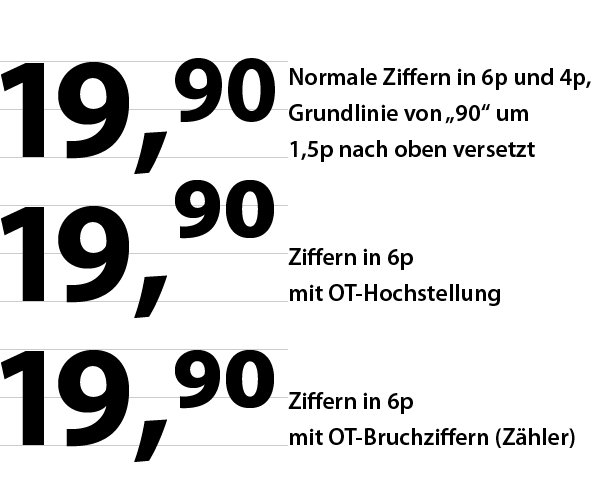
Suche Schrift um Preis auszuzeichnen
ich suche eine geeignete Schrift um Preise auszuzeichnen, siehe Beispiel.
Hat Jemand eine Ahnung welche Schrift in der Grafik verwendet wurde?
Du könntest drauf achten, dass die Schrift OpenType-Ziffern für Brüche und/oder Hochstellung hat. Kombiniert mit einem Zeichenformat wäre das dann ganz einfach. Anbei die Myriad Pro als Beispiel:
Vielen Dank, habe so nun die FF Unit gefunden.. auch eine sehr schöne Schrift.